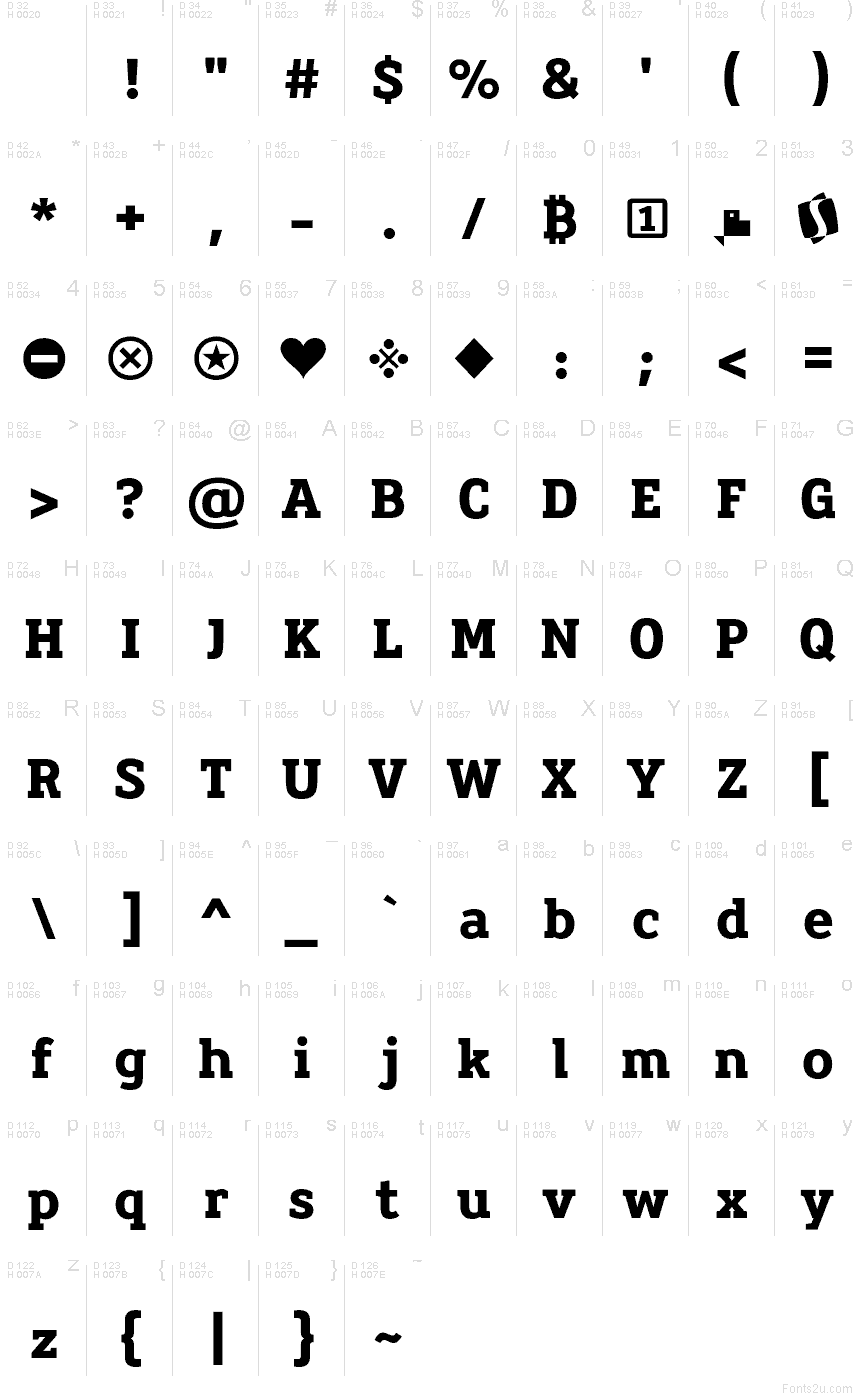
Biotrip Serif Bold
Biotrip Serif Bold da deFharo é uma fonte serifada gratuita definida por uma silhueta ampla e escura e serifas arredondadas, que dão às letras uma presença robusta, quase almofadada. Em vez de parecerem nítidas ou delicadas, as formas são densas e compactas, com curvas suaves que mantêm a textura longe da rigidez.
Essa combinação dá aos títulos curtos um papel de destaque em cartazes, capas de livros, embalagens e cabeçalhos onde um bloco de texto forte é necessário. A fonte adapta-se especialmente a projetos que precisam de letras serifadas com mais massa gráfica do que uma fonte de texto clássica, sem cair no aspeto simplório de uma slab.
Biotrip Serif is a friendly typeface family that is, above all, a journey. A journey (Trip) from the purity of geometry to the warmth of the organic (Bio).
Biotrip Serif comprises 14 methodically designed fonts, distributed across 2 styles (Regular and a genuine, flowing Italic) and 7 weights, ranging from the ethereal elegance of Light to the powerful impact of Black.